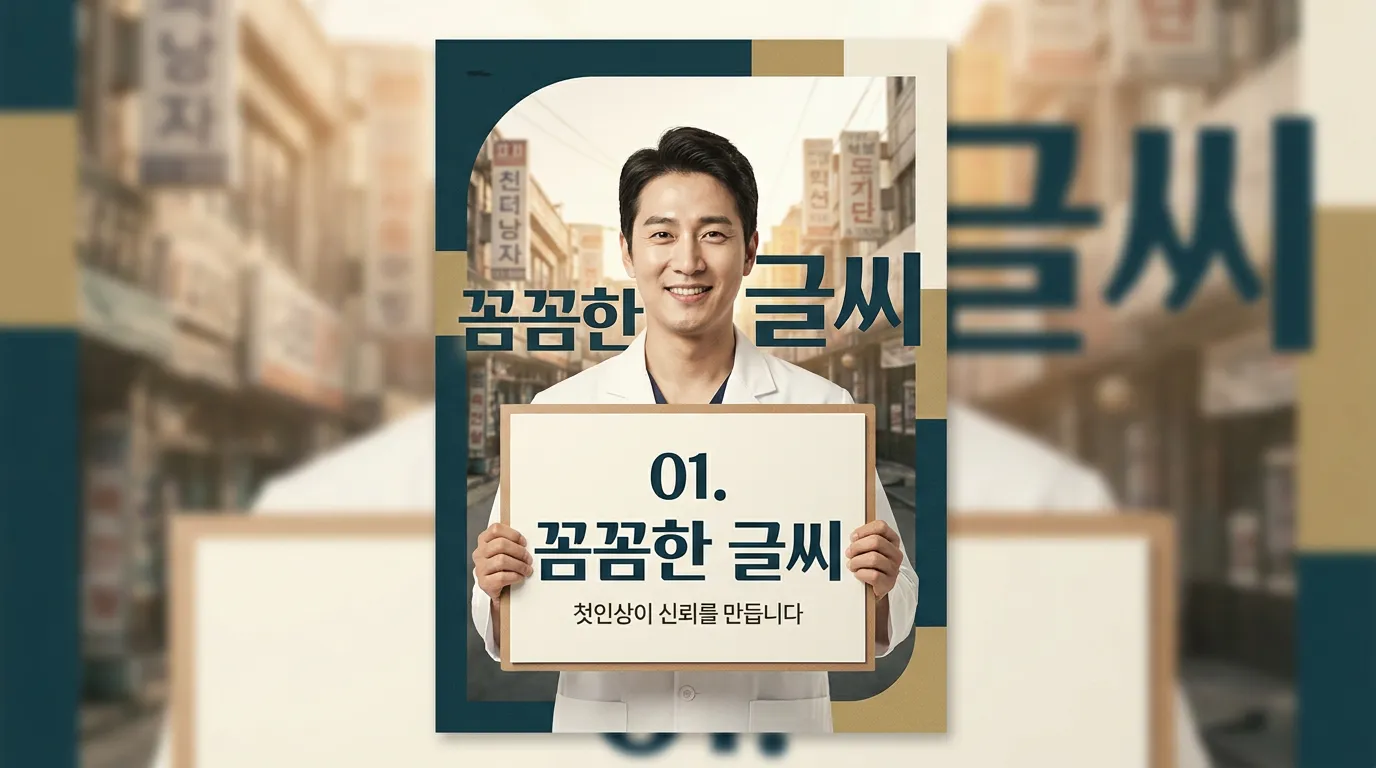
치과 로고 폰트, 환자가 ‘꼼꼼하다’고 느끼는 글씨에는 공통점이 있습니다
치과 로고 폰트 선택 전 봐야 할 서체 예시와 피해야 할 글씨체 5가지를 실무 기준으로 정리했습니다.
예약 전화를 걸기 전, 환자는 이미 로고의 글씨를 보고 ‘여기 대충 하진 않겠네’ 또는 ‘왠지 가벼워 보이네’를 판단합니다.
환자는 왜 글씨에서 진료 태도를 읽을까요?
치과 로고 폰트는 예쁜 글씨를 고르는 일이 아닙니다. 환자가 치료 전 느끼는 불안을 얼마나 낮춰줄지 정하는 첫 단서입니다. 특히 치과는 통증, 비용, 과잉진료 걱정이 같이 따라옵니다. 그래서 글씨가 너무 귀엽거나 과하면 환자는 원장님의 실력보다 ‘분위기’를 먼저 의심합니다.
기초조형학연구의 「서체 디자인 요소 변화에 따른 인상 연구」를 보면, 서체의 굵기, 기준선, 엘리먼트가 인상 형성에 영향을 준다고 정리합니다. 저는 이 대목이 치과 로고에 그대로 적용된다고 봅니다. 획이 일정하고, 글자 사이가 숨 쉬고, 기준선이 안정된 폰트는 ‘꼼꼼하게 맞춰진 병원’처럼 보입니다.
‘꼼꼼하다’는 느낌은 어떤 폰트에서 나오나요?
저라면 원장님 치과 로고에는 먼저 정제된 고딕 계열을 놓고 봅니다. 예를 들면 Noto Sans KR, Pretendard, Spoqa Han Sans Neo처럼 획 대비가 크지 않고 자소 구조가 깨끗한 서체입니다. 단, 그대로 쓰기보다 자간, 획 끝, 받침의 무게를 조정해야 로고가 됩니다.
핵심은 ‘얇고 세련된 글씨’가 아닙니다. 너무 얇으면 임플란트·교정·보존치료처럼 정밀한 진료의 밀도가 빠져 보입니다. 반대로 너무 두꺼우면 섬세함보다 광고 전단 느낌이 납니다. 치과 로고는 Regular와 Medium 사이, 혹은 Medium을 살짝 다듬은 무게가 가장 안전합니다.
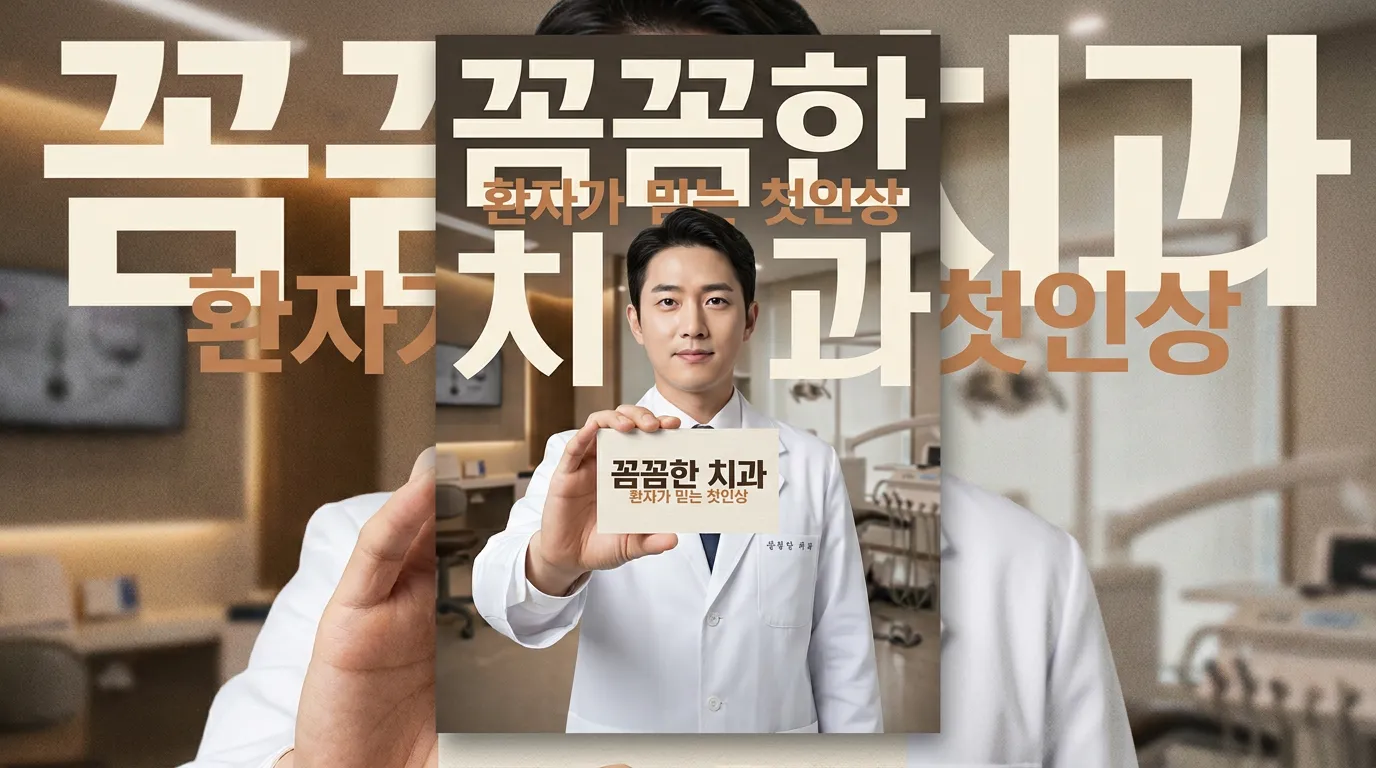
피해야 할 서체 5가지는 무엇인가요?
첫째, 손글씨체입니다. 나눔손글씨류나 펜글씨 느낌은 소아치과 일부 콘셉트가 아니라면 진료의 정밀함을 흐립니다. 둘째, 궁서체와 붓글씨체입니다. 한방병원도 아닌데 ‘권위’만 앞서고 최신 장비나 섬세한 치료 이미지는 약해집니다.
셋째, 굴림체입니다. 굴림체 연구에서는 이 서체가 과거 Windows와 공문서 환경에서 널리 퍼졌고, 이후 간판·판촉물에도 많이 쓰였다고 설명합니다. 문제는 익숙함이 곧 브랜드가 되지는 않는다는 점입니다. 환자 눈에는 ‘직접 만든 로고’처럼 보이기 쉽습니다.
넷째, 초두꺼운 제목체입니다. Black Han Sans 같은 강한 제목용 서체를 그대로 쓰면 치과보다 할인 행사 배너에 가까워집니다. 다섯째, 너무 좁고 각진 영문 서체입니다. Implant, Dental Clinic 같은 영문을 Impact류로 넣으면 정밀함보다 압박감이 먼저 옵니다.
폰트를 고른 뒤에는 어디를 봐야 하나요?
폰트 이름보다 먼저 봐야 할 건 ‘작게 줄였을 때’입니다. 명함, 예약 문자 이미지, 네이버 플레이스 썸네일에서 로고가 흐려지면 좋은 폰트가 아닙니다. 병원 진료 안내 디지털 사이니지 개선 연구에서도 글씨 크기 확대, 배경 단순화, 대비 강화 뒤 가독성 만족도가 가장 많이 올랐다고 나옵니다. 로고도 같습니다. 작아졌을 때 읽히는 글씨가 오래 갑니다.
마크에서 치과 로고를 볼 때도 예쁜 시안 하나로 끝내지 않습니다. ‘치과의 이름이 얼마나 또렷한가’, ‘심볼보다 글자가 먼저 믿음을 만드는가’, ‘간판이 아니라 앱 아이콘 크기에서도 버티는가’를 같이 봅니다. 결국 환자는 멀리서 심볼을 보고, 가까이서 글씨를 확인합니다.